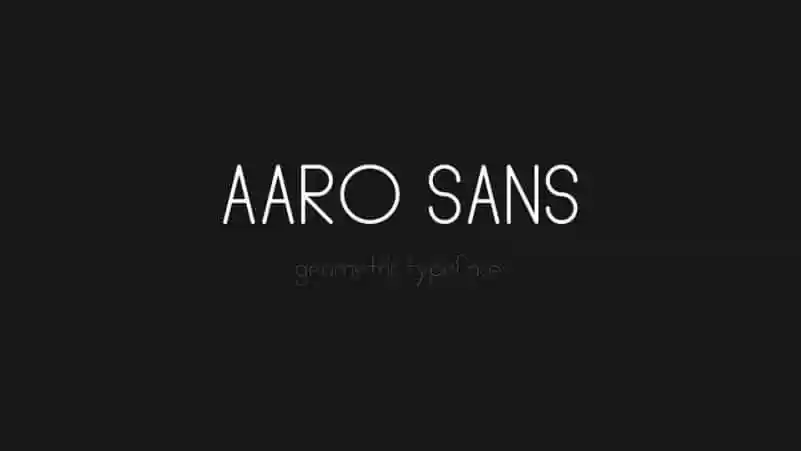
Aaro Sans Serif é uma elegante tipografia redonda com duas densidades. Esta fonte combina modernidade, beleza e simplicidade perfeitamente. Foi criada pelo designer de fontes Aaron Troglia. A família de fontes tem um aspecto geométrico arredondado em várias densidades: Hairline e Regular. Foi projetada especialmente para exibir com impacto dramático. É uma escolha ótima para designers que valorizam tanto a simplicidade quanto a elegância, querendo destacar o texto em ambientes de design visual interessantes. Não perca tempo, instale Aaro Sans Serif e experimente como ela enriquece suas composições digitais.